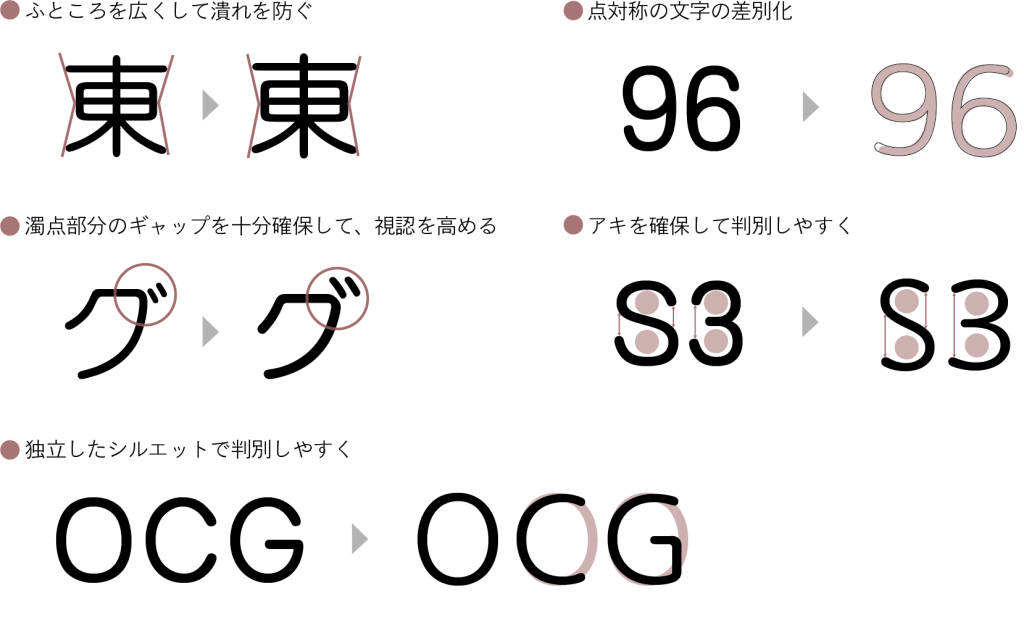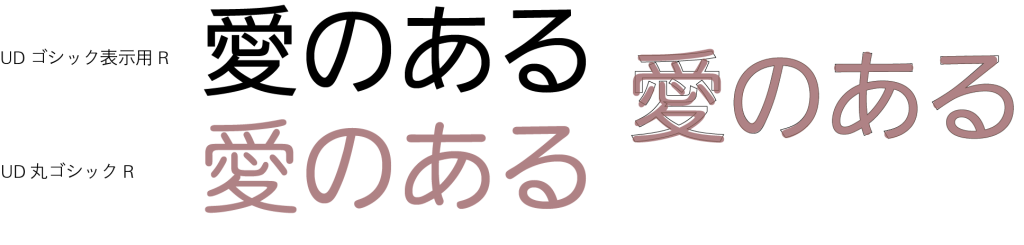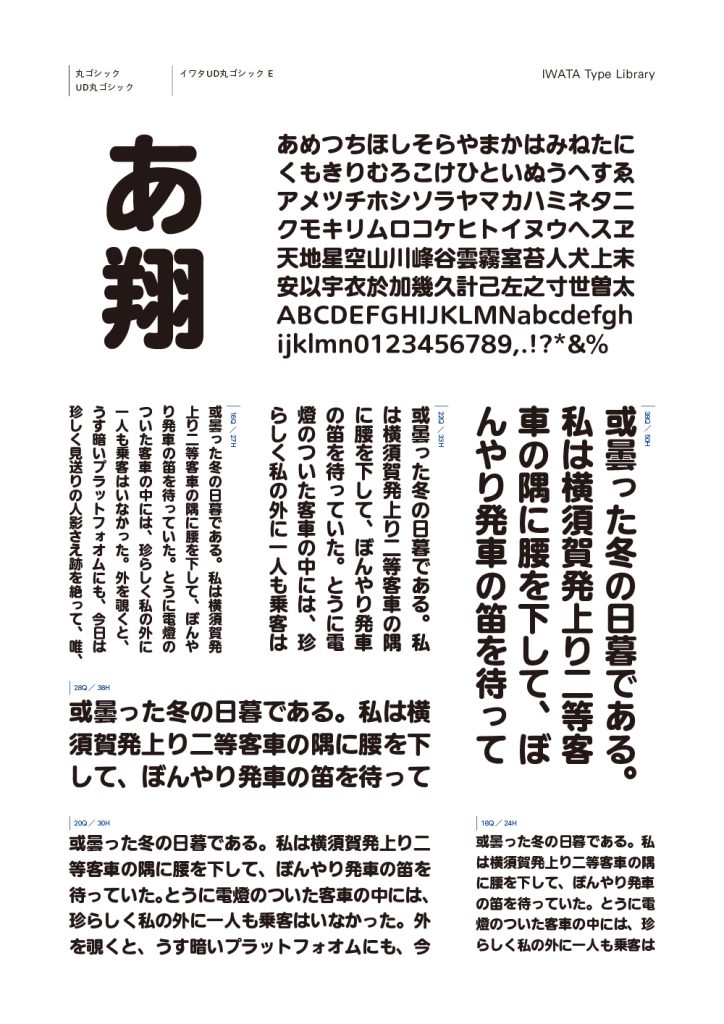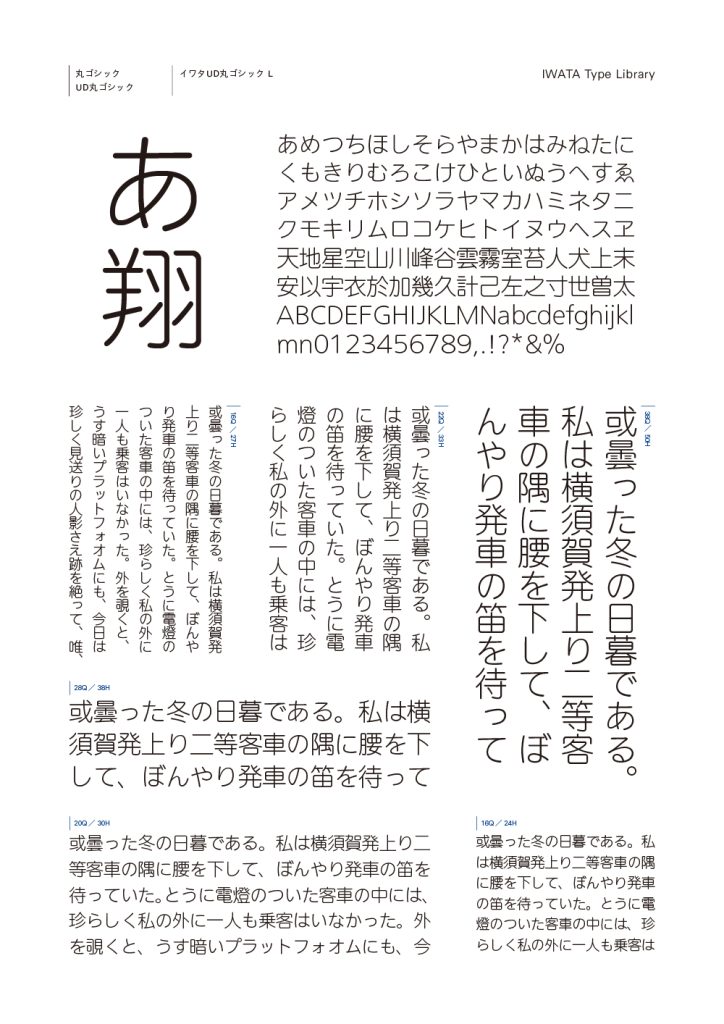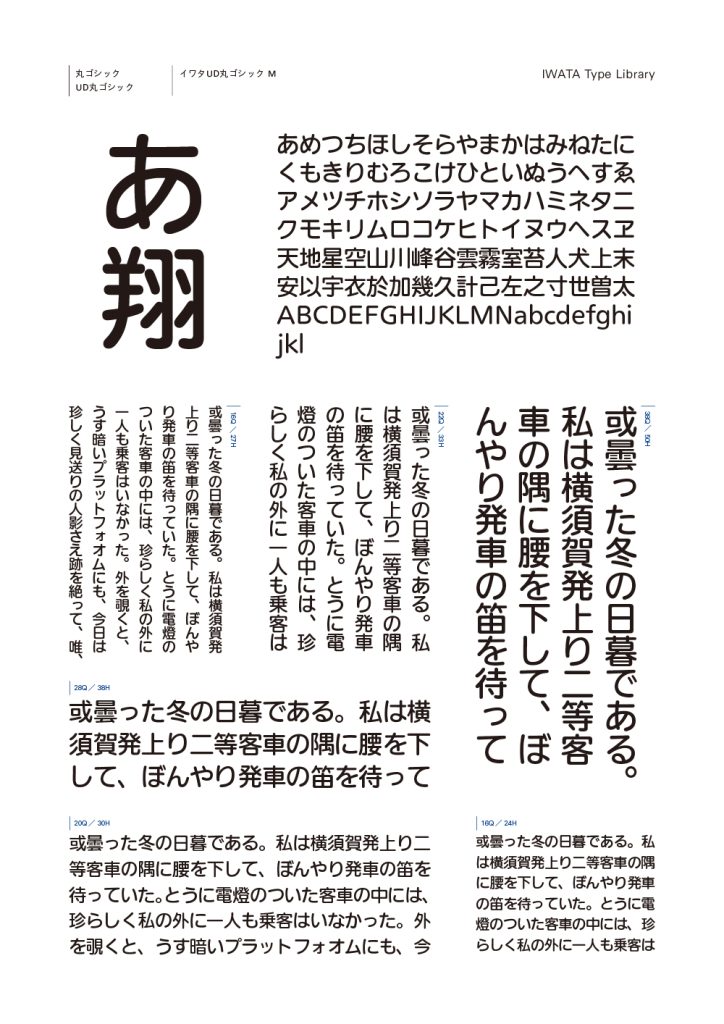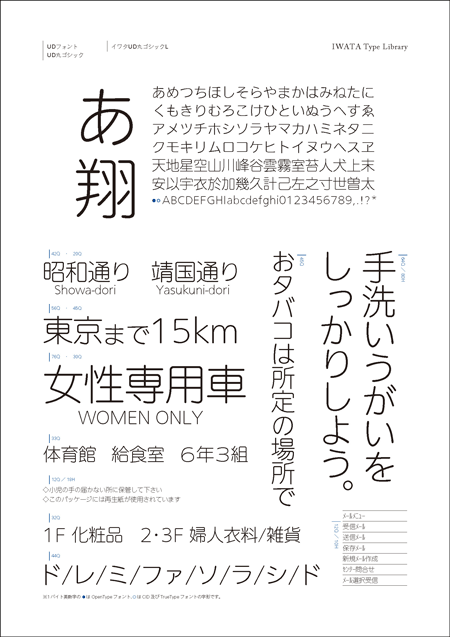
松下電気株式会社(現、パナソニック株式会社)と共同で開発したUD ゴシックと同じコンセプトで設計している丸ゴシック体です。仮名や英数字は視認性と判読性に重点を置いて大きくデザインし、見出しや短い文章での使用に向いています。
開発の背景
高齢化社会が進んだ現在、老眼、白内障等々、加齢による視力の低下に悩む人が急増しています。
一方で製品の多機能・高機能化、小型化、デジタル化が急速に進んでいます。 このような環境においては、文字こそUD の視点で作られたものが必要と考え、誰にとっても読みやすい文字、「イワタUD フォント」を開発するに至りました。
書体デザインのポイント
誤読を防ぎ読みやすさを向上させるために、デザインにいくつもの工夫がされています。
※「イワタ丸ゴシック体M」と「イワタUD 丸ゴシックR 」を比較しています
UD 丸ゴシックは先行して作成したUD ゴシックと同じコンセプトで設計しています。